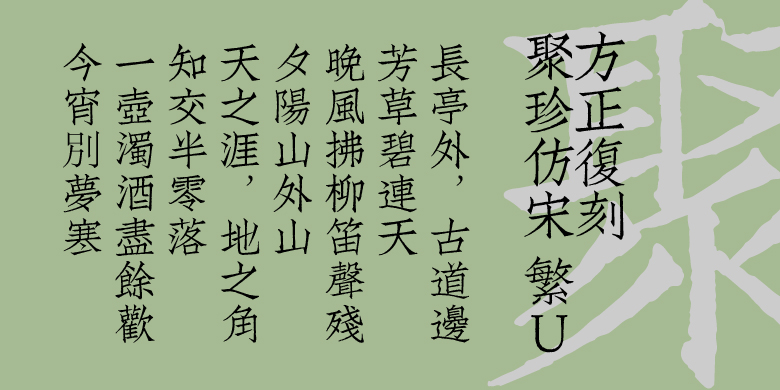
方正復刻聚珍仿宋
张璋
仿宋
方正复刻聚珍仿宋是字形略长,笔画粗细均匀,起笔处有斜势棱角,折笔处棱角分明,整体风格刚柔并济、挺拔清秀。该字体是依据《上海中华书局聚珍仿宋体头号字样本》的完全复刻,笔形上和现有标准不能保证完全一致,请使用者注意。 聚珍仿宋是1916年丁善之、丁辅之兄弟创制的,被视为中国第一款现代印刷字体。其笔画横竖粗细均匀,字形清秀挺拔。